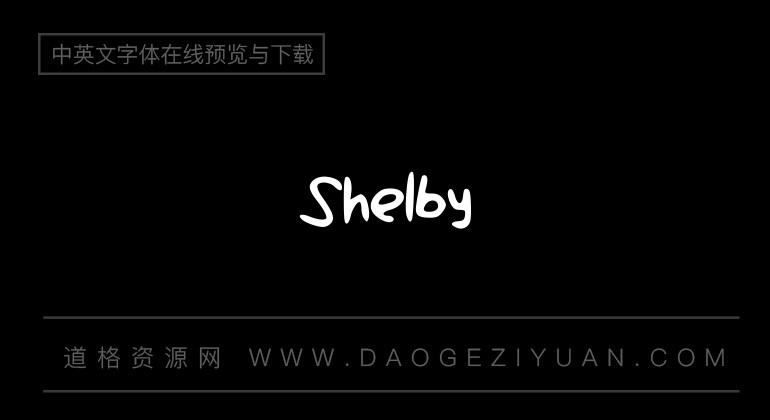
Shelby 字体是一种抽象字体,由英国设计师 David Jonathan Ross 设计。它的特点是自由的线条,具有良好的可读性和可辨认性,可以用于各种不同的应用场景,如标题、广告、书籍和网页等。它的字体结构更加灵活,可以适应不同的应用需求,并且可以自由混合,以创造出多种不同的形式。内容介绍
Shelby是一款非常不错的手写艺术字体,具有很好的视觉感,适合于文化类的宣传设计、商业类品牌的广告和产品包装设计以及个性化文字排版等较多场景。